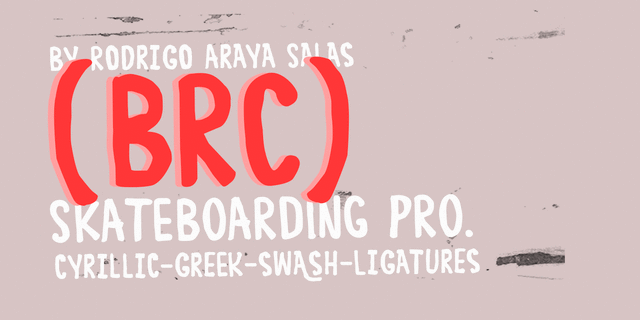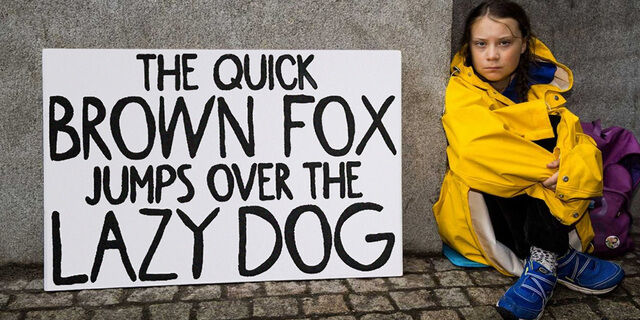
BRC – неформальный рукописный шрифт со смелым уличным настроением с поддержкой множества европейских языков, а также кириллицы и греческого. Этот шрифт имеет богатые возможности в виде альтернативных глифов, росчерков и редких лигатур. Шрифт BRC разработал Родриго Арая Салас в 2014 году.
уличный, бытовой, городской, смелый, крафтовый, неформальный, мультяшный, ручной, экономный, наивный, рукотворный, кустарный, самодельный, высокий, оригинальный, живой, характерный, игривый, заметный, домашний, выразительный, неряшливый, подвижный, непоседливый, ремесленный, хулиганский, забавный, милый, дерзкий, опасный, экстремальный, артизанальный, небрежный, кричащий, вернакулярный, динамичный